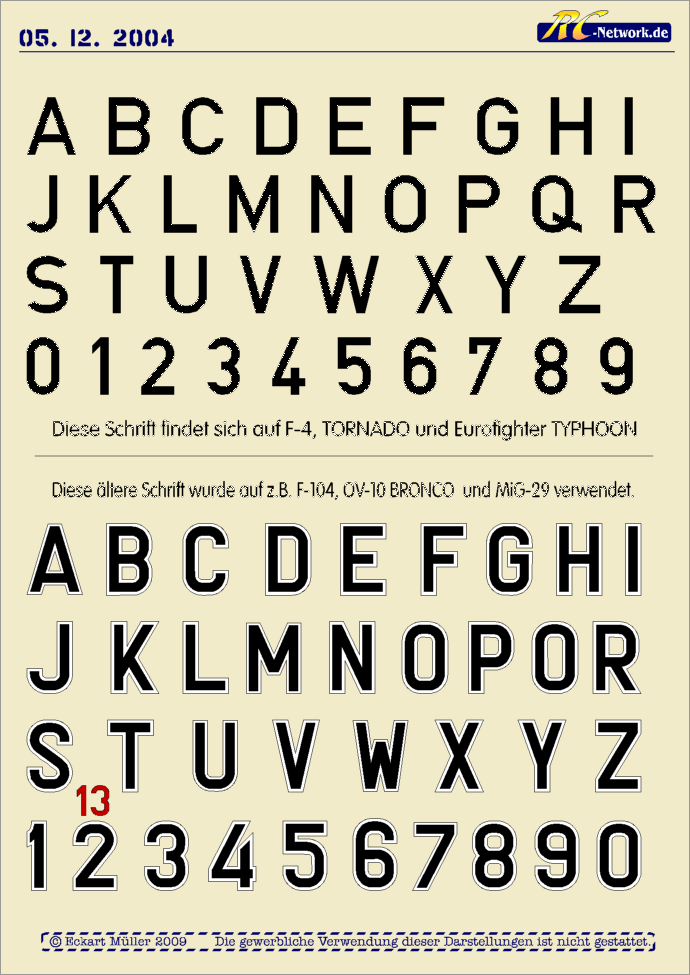
Welche Schrift ist das? (Schlafwagen)
Der Vollständigkeit halber möchte ich noch auf die (leider nicht allzu günstige) Idlewild verweisen.
Hallo StefanB..Preis konnte ich jetzt nicht sofort sehen..vielleicht kennst du ihn ja. aber in der Tat..die kommt auch sehr nah ran. Es ist schon verdammt schwer..diese als ungeübter auseinanderhalten zu können. Da braucht man ja fasst einen Fadenzähler um die Unterschiede genau zu identfizieren. Ich hätte mal Graphologe werden sollen ..ach nee die machen ja nur Handschriften ;-)
Oder geht es hier um die Renovierung von Museumswagen? So eine Anfrage hatte ich vor einiger Zeit im Zusammenhang einer Anpassung der DIN 1451 in einigen wenigen Buchstaben bei den Anschriften eines alten Reichsbahn-Wagen.
Auch beim Mitropa-Wagen scheint mir die lateinische Schrift auf der DIN zu basuieren, jedoch irgendwie zwischen Mittel- und Breitschrift zu liegen, also auch speziell gezeichnet. Allerdings wundert mich die doch extrem in ihrern Formen abweichende kyrillische Schrift mit starkem Strichkontrast.
Ja Peter..Mitropa zu DDR-Zeiten hat das genommen was da war ;-) ok ich überspitze natürlich..aber du hast recht.
Kyrillisch deswegen, weil ja die DR der DDR auch Mitglied im Eisenbahverbund des OSShD (http://de.wikipedia.org/wiki/Organisation_f%C3%BCr_die_Zusammenarbeit_der_Eisenbahnen)war. Somit konnte man an Schildern oft deutsche, französische italienische und russische Texte lesen (siehe auch Beschriftung Reisezugwagen innen und außen).
Ach so, die Mitropa-Schrift (vom Logo) habe ich als "Midroba" nach den original-Zeichnungen deer preußischen Eisenbahnverwaltung gezeichnet.
Ja Peter deine Schriften sind immer eine Reise auf deine Seite wert. Wir hatten schon mal per Mail Kontakt da ging es um Schriften die auf dem Schild am CheckPointCharlie in Berlin zu sehen sind. Da hat sich noch kein Schriftdesigner getraut die der Nachwelt zu hinterlassen. Ist ja auch eine Schrift, die damals noch per Hand gemalt wurde. Wie viele Gebrauchsschriften nach dem Krieg Gebrauchsgrafiker Plakate entworfen haben..usw.
Mir kommt es so vor, dass die Schriften der Ungarische Eisenbahn auf die Schriften der DIN 1451 basieren. Also Engschrift, Mittelschrift und Breitschrift. Formal gesehen haben die drei nie richtig zusammengepasst. Daher liegt es auf der Hand dass es sich hierbei, je nach dem was für Kriterien man anwendet, um veränderte, verbesserte oder vielleicht sogar verschlimmbesserte Version der DIN Schriften handelt. Die Deutsche Reichsbahn führte auf den Personenwagen der Rheingold-Züge in den 1930er Jahre einen DEUTSCHE REICHSBAHN-Schriftzug der vielleicht Modell stand für die DIN Breitschrift. Die RHEINGOLD-Schriftzüge selbst waren eckiger, in etwa wie die spätere Eurostile. Ich kann es mir gut vorstellen, dass andere Eisenbahngesellschaften bzw. sich gerne an diese Schriftbilder orientiert haben.
Ah ha auf die Schrift wäre ich glaube ich nie gekommen muss ich mal austesten.
Das kyrillische Beschriftung in Russisch gerade bei Wagen in internationalen Verkehr eine Selbstverständlichkeit waren, ist mir schon klar.
Um so mehr wundert es mich. das man hier, besonders wenn dieser Text in einer Reihe mit den anderssprachigen Anschriften auftaucht, keine Schriftart gefunden hat, die im Duktus zu den anderenb Textten past. Ich habe ja auch in vielken meiner Schriftenb auch kyrillische Schriftzeichen mit drin, da ist es eigentlich kein problem, diese optisch passend hin zu bekommen, ohne das diese dann an Lesbarkeit einbüßen.
Gerade bei der Mitropa und der DR sollte das eigentlich kein Problem sein - hier ist man dies doch eigentlich gewohnt.
Zu den Berlin-Schildern: Da hate ich gerade aus der Nachkriegszeit Filme gesehen, in denen Schilder waren, die sich von der russischen Kommandantur an die Berliner Bevölkerung richteten. Sehr saubere Schildermaler-Arbeit, aber man sah der lateinischen Schrift deutlichst an, das der Schreiber eindeutig aus der kyrillischen Tradituioin kam, was der Schrift einen durchaus eigenen Charakter gibt. Schade, das ich hiervon kein Standbild bekommen konnte.
Bei ’ner Suche nach den beiden untenstehenden Begriffen findet man viele Modellbahnwagen; vielleicht ist da noch was passendes bei.
he he ist ja schon komisch wie zwei "doofe " auf den selben gedanken kommen. Nachdem ich auf den einem Bild das ungarische Wort für Schlafwagen gelesen hatte ging ich auch auf die Suche... Oft findet mal viel mehr information über ein Thema wenn man dort landestypische Begriffe eingibt. Wenn Google Translate besser wäre würde man wohl noch viel mehr finden.
Ich meinte hier auch nur die obere von den beiden, nicht die untere mit den weißen Rändern. Zumindest hat diese auch diesen DIN-Charakter in etwas weiter als Mittelschrift, aber nicht so weit wie die Weitscxhrift
Noch mehr „Breitschrift“ auf Eisenbahnwagen:
Und einiges zur MAVSZ 2941, die DIN-ähnliche Normschrift der ungarische Eisenbahngesellschaft.